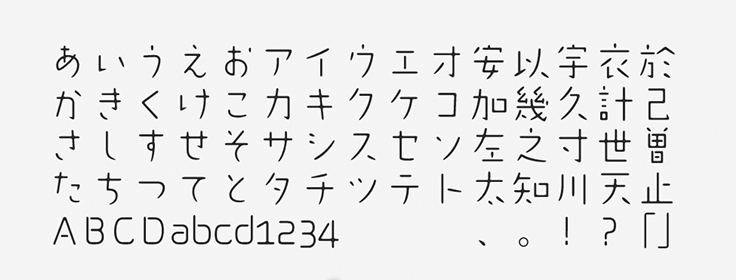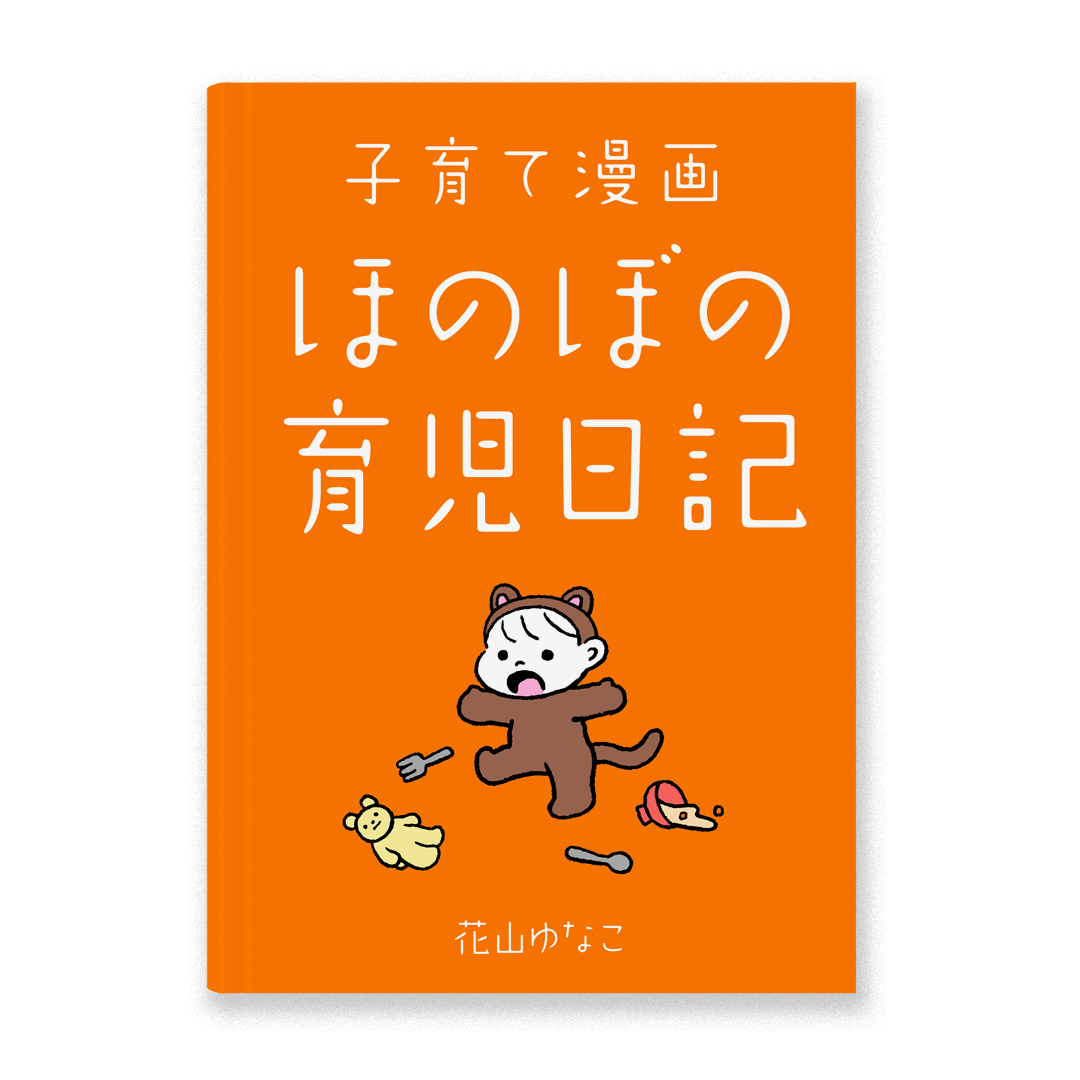
力の抜けたような適度な “ゆるさ” が魅力! 文字の中に大胆な余白がある「はるひ学園」の活かし方
~<主要なオススメ用途>タイトル・見出し、絵本、雑誌、ロゴなど~
【はるひ学園 作例】育児漫画のタイトルロゴ
「はるひ学園」について
七種泰史氏による「学園」をベースに開発され、2007年にリリースされました。「学園」は、1999年の第6回国際タイプフェイスコンテスト モリサワ賞の金賞を受賞したタイプフェイスデザインです。素朴な可愛らしさと力の抜けた楽しさのイメージを備えています。
「はるひ学園」の特徴
縦画や横画はまるでロゴのように直線を基本としてデザインされていますが、エレメントどうしが接するあちこちの箇所にたっぷりと大胆な余白が設けられており、堅すぎる印象はまったくありません。エレメントの先端や内角は丸く処理されており、柔らかな雰囲気が強められています。
飾り気のないストロークで、現代において求められやすい適度な “ゆるさ” が大きな魅力です。どこかユーモラスで、ふっと息を抜けるような人間味にあふれています。
はるひ学園は、肩肘を張らずに読んでもらうような媒体に適した、ほのぼのとした雰囲気があります。私も昔から愛用しているフォントです。「はるひ学園」という名前も秀逸ですね。ロゴデザインの参考にもなる特徴的なフォントです。
作例のポイント拡大
●書体名:「はるひ学園」
●書体の分類:「デザイン書体」
●カテゴリ:「素朴」「可愛い」
よく使われるシーン
タイトル・見出し、雑誌、絵本、ロゴ、POP
「はるひ学園」の書体情報
【はるひ学園】書体見本